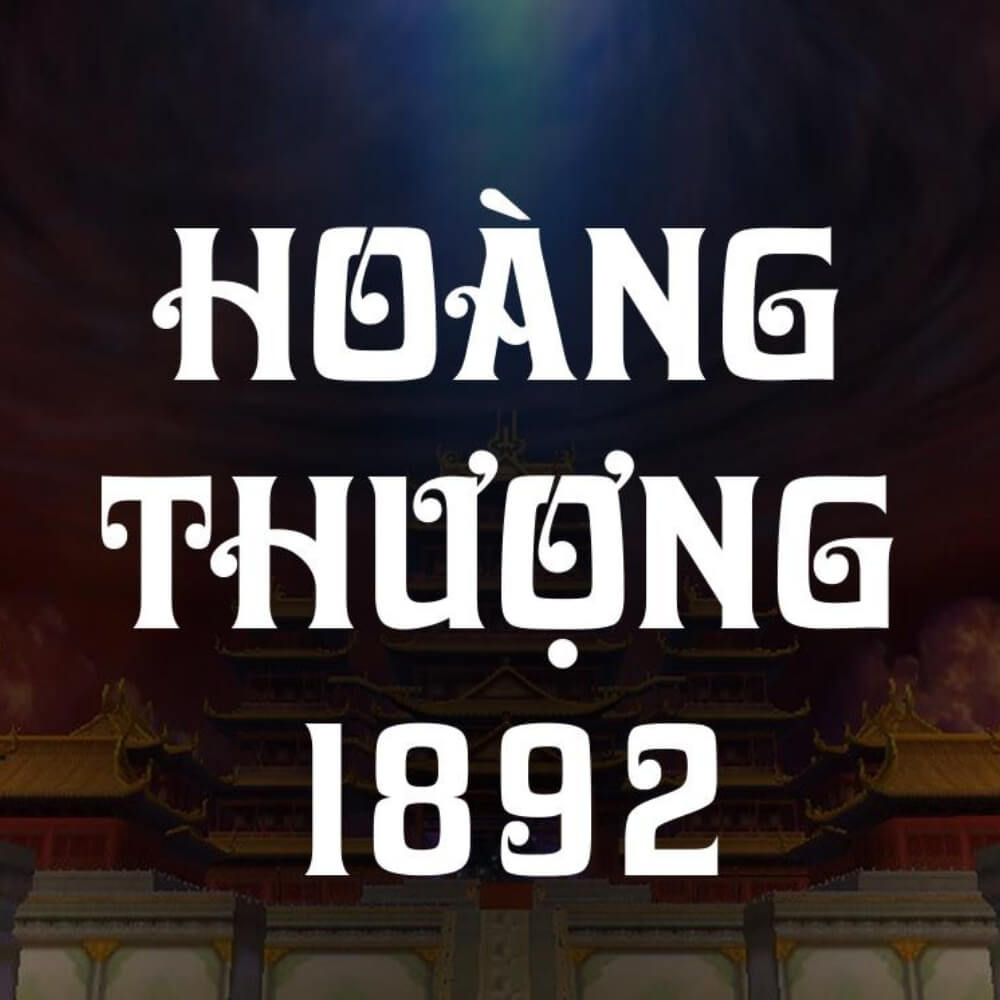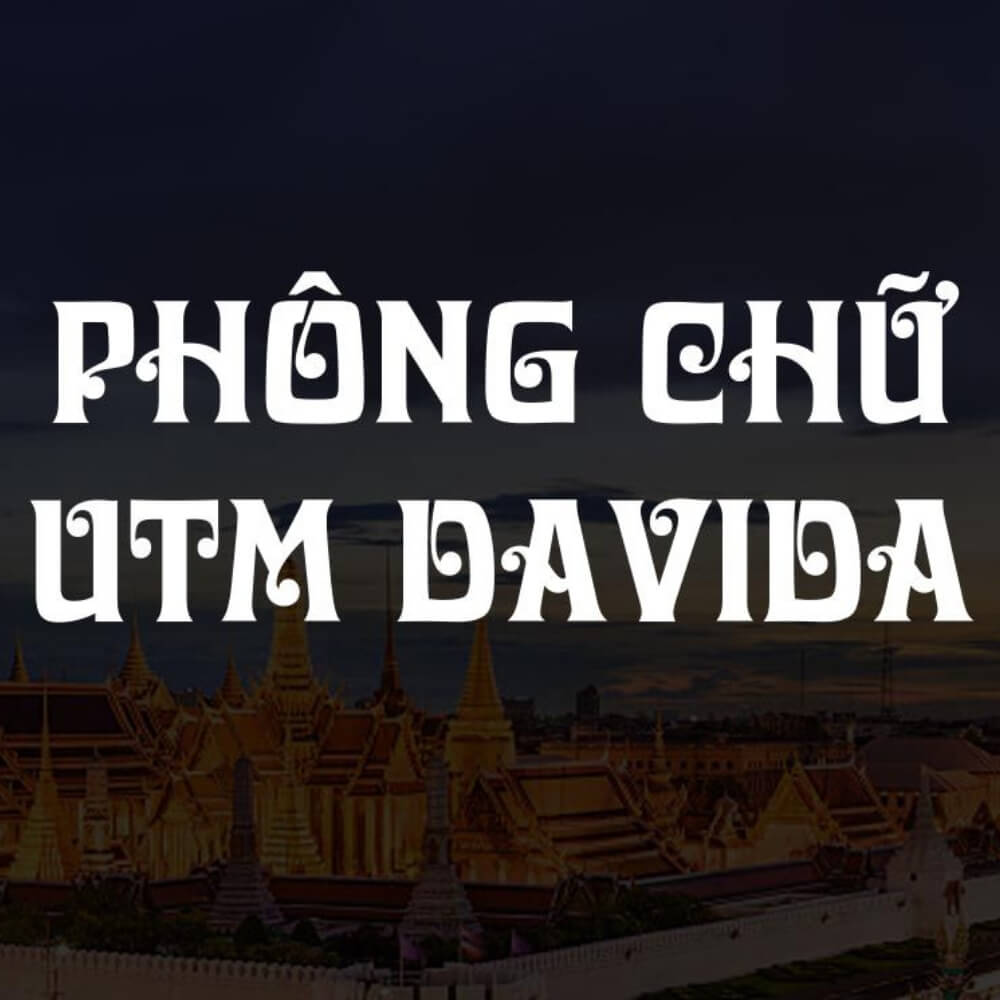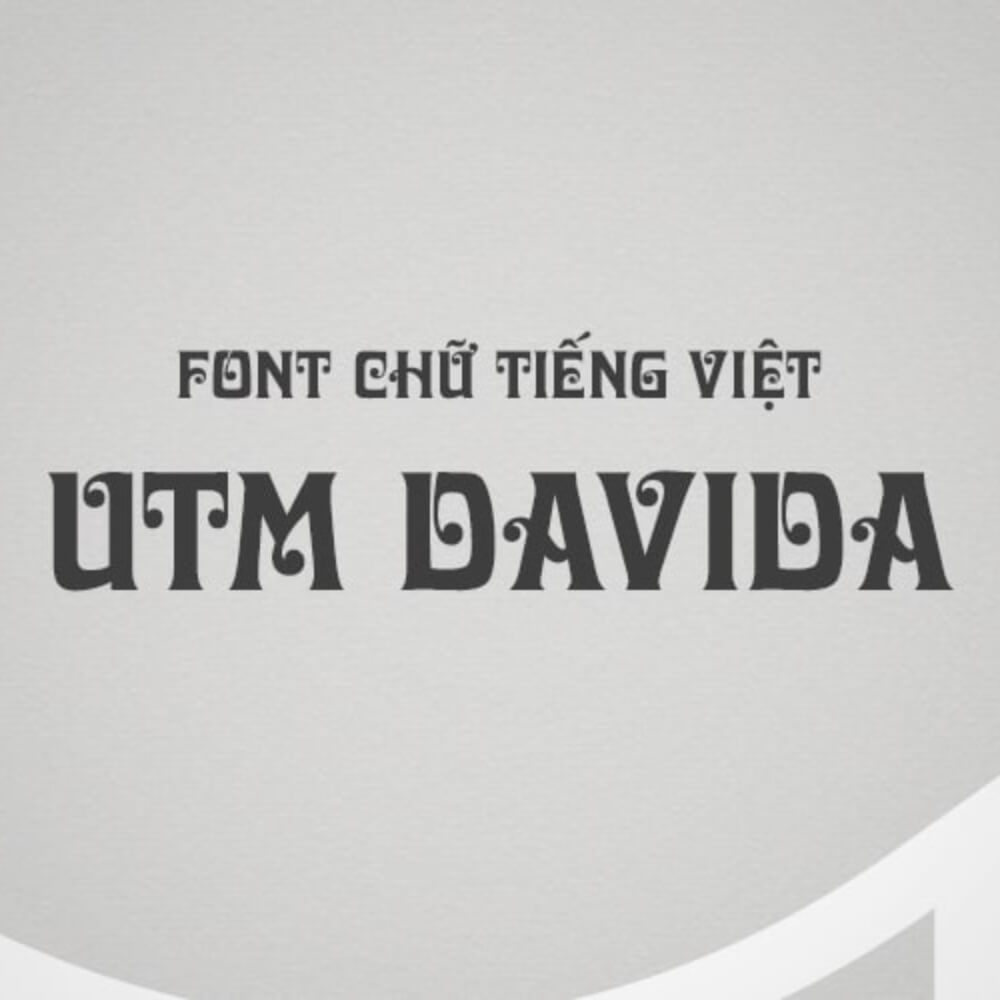
Không ít người khi tìm font việt hóa UTM Davida thường gặp tình trạng tải về nhưng chữ bị lỗi dấu, thiếu ký tự tiếng Việt hoặc font hiển thị sai trong phần mềm thiết kế. Nhiều file chia sẻ trên internet thực chất chỉ là phiên bản cũ hoặc chưa việt hóa hoàn chỉnh, khiến việc thiết kế logo hoặc poster trở nên khó khăn.
Tên font UTM Davida
Kiểu chữ Display / Decorative
Hỗ trợ Tiếng Việt đầy đủ
Ứng dụng Logo, poster, tiêu đề
Bộ font davida việt hóa thường được sử dụng trong các thiết kế cần phong cách chữ trang trí độc đáo. Nhờ hình dạng chữ đặc trưng, font này giúp tiêu đề nổi bật hơn trong nhiều loại ấn phẩm.
Đặc điểm nổi bật của font việt hóa UTM Davida
Trong nhóm font trang trí, font việt hóa UTM Davida được nhiều designer lựa chọn nhờ cấu trúc chữ độc đáo và dễ tạo điểm nhấn thị giác. Khác với các font sans-serif đơn giản, Davida mang phong cách nghệ thuật và cá tính hơn.
Một số đặc điểm nổi bật của font này gồm:
• Nét chữ uốn cong độc đáo.
• Phong cách chữ trang trí nổi bật.
• Phù hợp thiết kế logo và tiêu đề.
• Dễ tạo điểm nhấn cho poster quảng cáo.
Nhờ những đặc điểm này, font việt hóa UTM Davida free download thường được sử dụng trong các thiết kế mang phong cách sáng tạo hoặc nghệ thuật.
Font chữ UTM việt hóa hỗ trợ tiếng Việt rõ ràng, dễ sử dụng
Ứng dụng của font Davida UTM
Nhờ kiểu chữ trang trí đặc trưng, font việt hóa Davida có thể ứng dụng trong nhiều lĩnh vực thiết kế khác nhau. Font này đặc biệt phù hợp khi designer cần tạo tiêu đề nổi bật và khác biệt.
Ứng dụng font Davida trong thiết kế:
• Thiết kế logo: font Davida giúp thương hiệu tạo dấu ấn riêng.
• Poster quảng cáo: tiêu đề nổi bật và dễ thu hút người xem.
• Banner sự kiện: font trang trí giúp thiết kế sinh động hơn.
• Typography: thường dùng cho các thiết kế nghệ thuật.
Ứng dụng font việt hóa UTM Davida trong in ấn:
Trong ngành in ấn, những font trang trí như font việt hóa UTM Davida thường được sử dụng trong nhiều sản phẩm truyền thông và quà tặng doanh nghiệp.
• In logo trên sổ tay.
• In slogan trên túi vải.
• Khắc laser trên bút kim loại.
• In UV trên bình giữ nhiệt.
03 lưu ý khi sử dụng font trang trí trong thiết kế
Font trang trí như font UTM Davida mang tính nghệ thuật cao, vì vậy designer cần sử dụng hợp lý để tránh làm bố cục thiết kế trở nên rối mắt.
• Không dùng cho đoạn văn dài: font trang trí chỉ nên dùng cho tiêu đề.
• Kết hợp với font đơn giản: pairing với sans-serif giúp bố cục cân bằng.
UTM Davida việt hóa hiển thị chuẩn, dễ áp dụng trong thiết kế
Font việt hóa UTM Davida là lựa chọn phù hợp cho các thiết kế cần sự sáng tạo và nổi bật. Khi sử dụng đúng phiên bản font việt hóa UTM Davida download, designer có thể đảm bảo chữ hiển thị đầy đủ dấu tiếng Việt và giữ được tính thẩm mỹ của thiết kế.